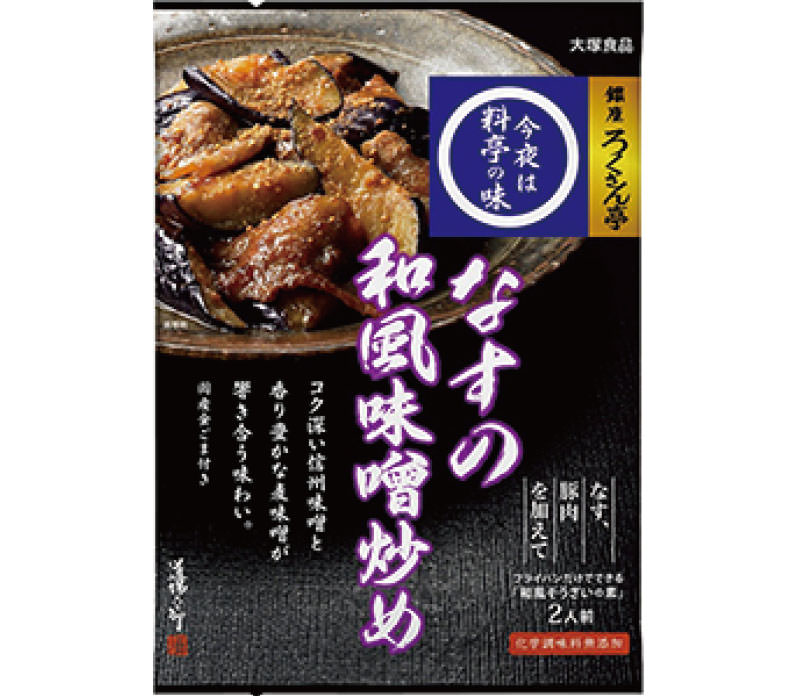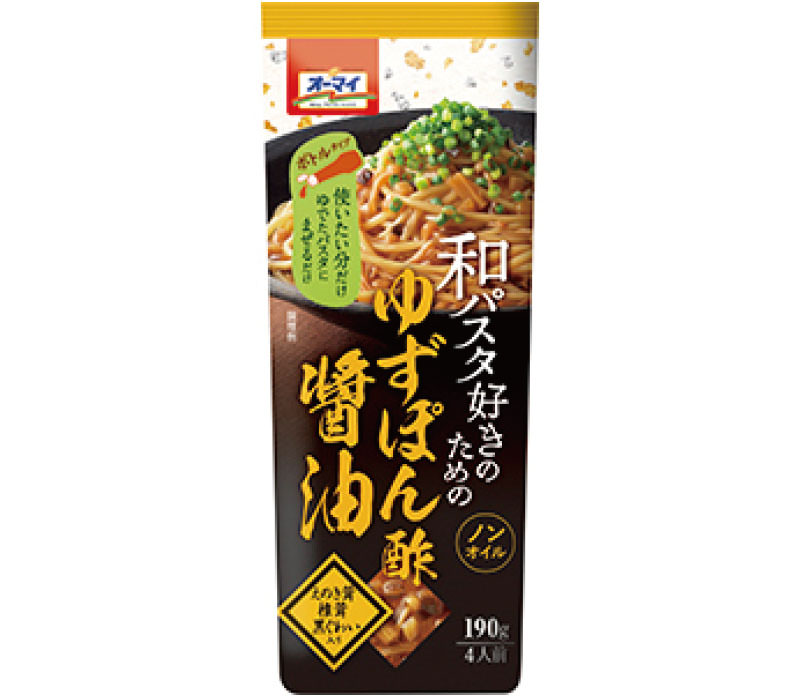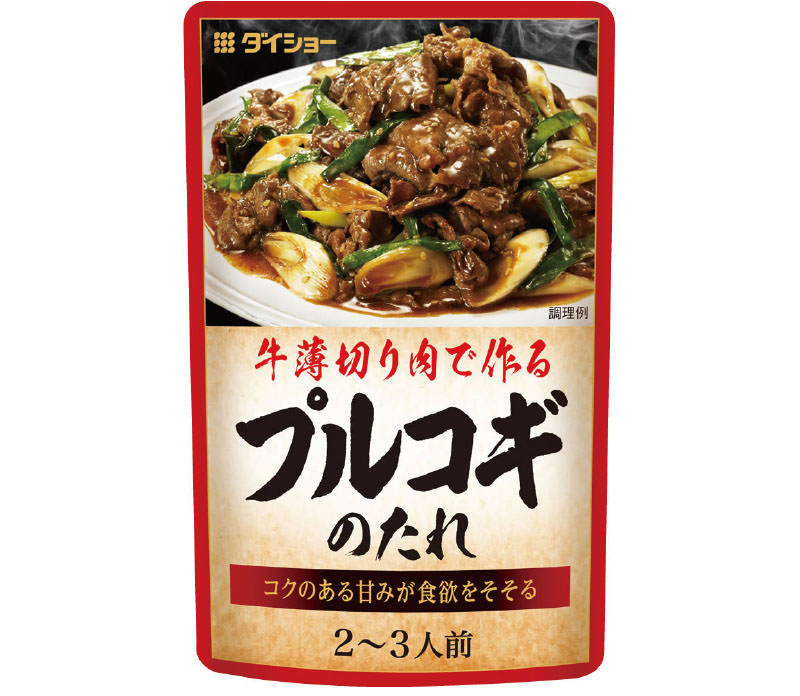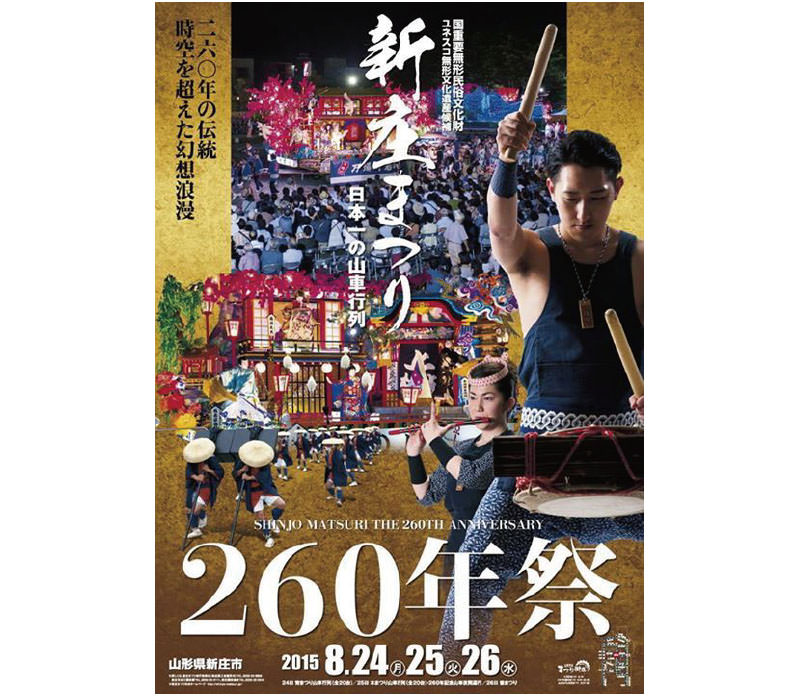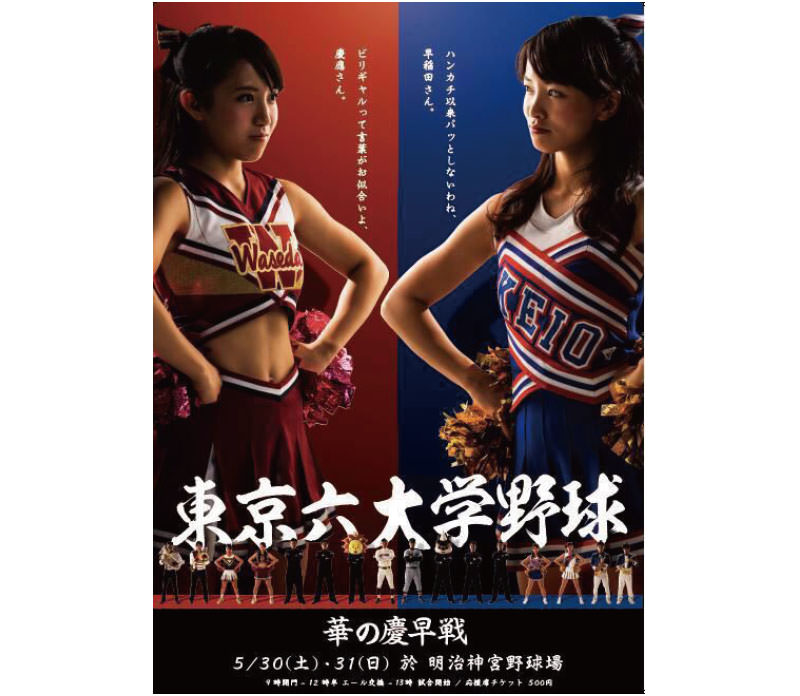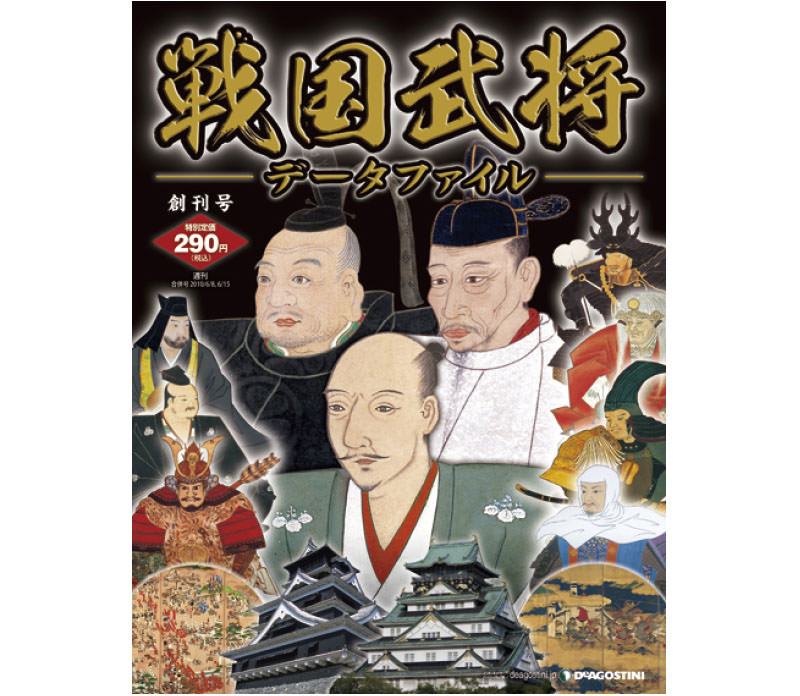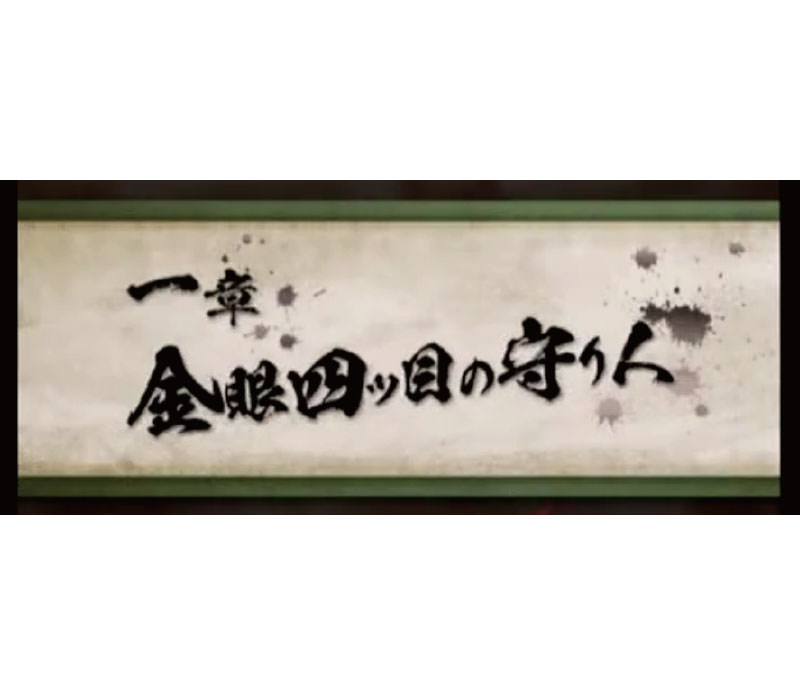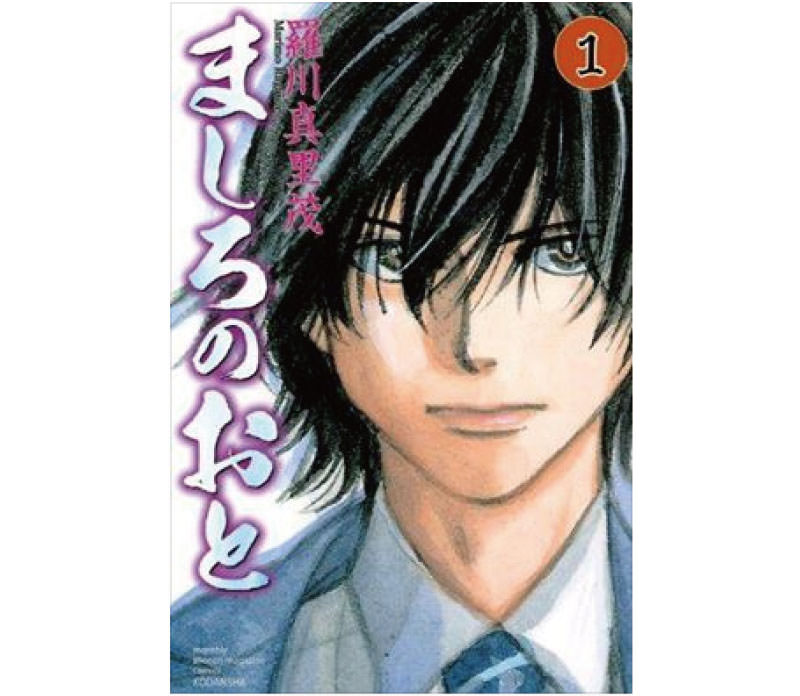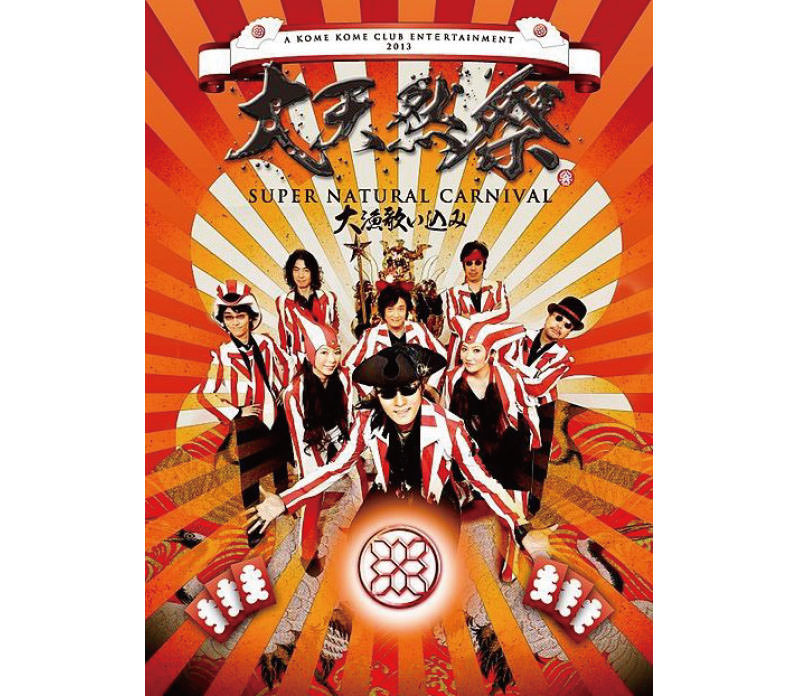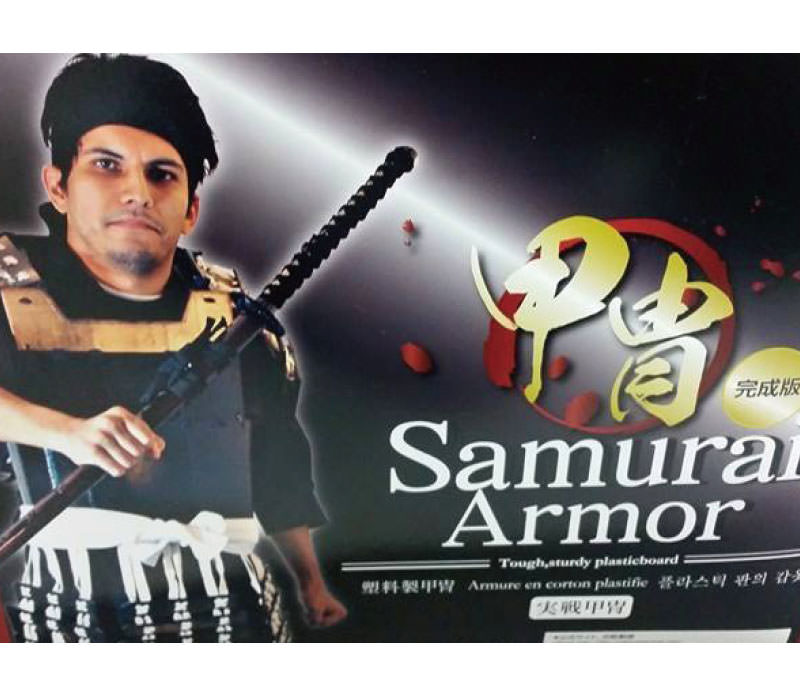
株式会社昭和書体により書家「綱紀栄泉(つなのりえいせん)」の書き綴った毛筆諸本をデジタル化した毛筆書体です。
その特徴は毛筆書体独特のかすれやにじみをより忠実に再現したもので、直筆と見分けがつかないほどの本格的な毛筆書体です。
一般書体よりも約5から50倍のデータポイント数で表現されるかすれやにじみ具合を実現した毛筆書体です。
主に力強いタイトルやキャッチコピーなどの利用に最適で、有名商品のタイトルなどへも多く利用されています。その他、POP、ちらし、DM、飲食店メニュー、和風を表現する媒体やコンテンツなどにも幅広くご利用いただけます。